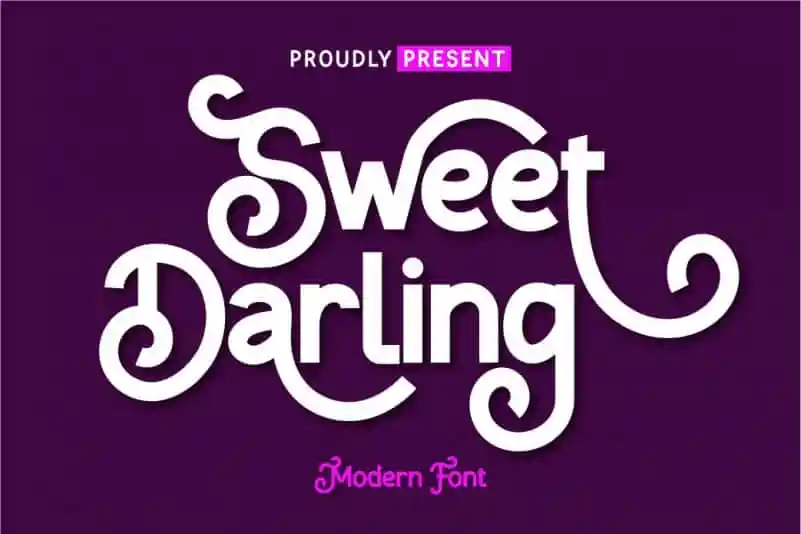
Sweet Darling Display Font – Download Grátis
A Sweet Darling Display Font é uma escolha ideal para projetos de design que precisam de um toque delicado e elegante. Seja você criando adesivos de promoção de alimentos, banners promocionais ou até mesmo cartões de boas-vindas personalizados em sua nova loja de vinhos – este fonte vai oferecer uma aposta segura. Suave e sofisticada, ela pode ser usada para dar um toque especial a suas propagandas e marcas, ou então aplicá-la como assinatura de uma publicação no Instagram sobre receitas criativas. Ela também é perfeita para designs de convites casamentos, criações de citações e até mesmo em textos para posters. Seja qual seja o projeto que você está trabalhando, esta fonte oferece um acabamento harmonioso e agradável sem deixar de ser original. Com seu designer atento às nuances da fonte, Twinletter trouxe essa opção à cena das fontes do tipo sans serif, permitindo que você personalize cada detalhe em sua próxima produção gráfica.